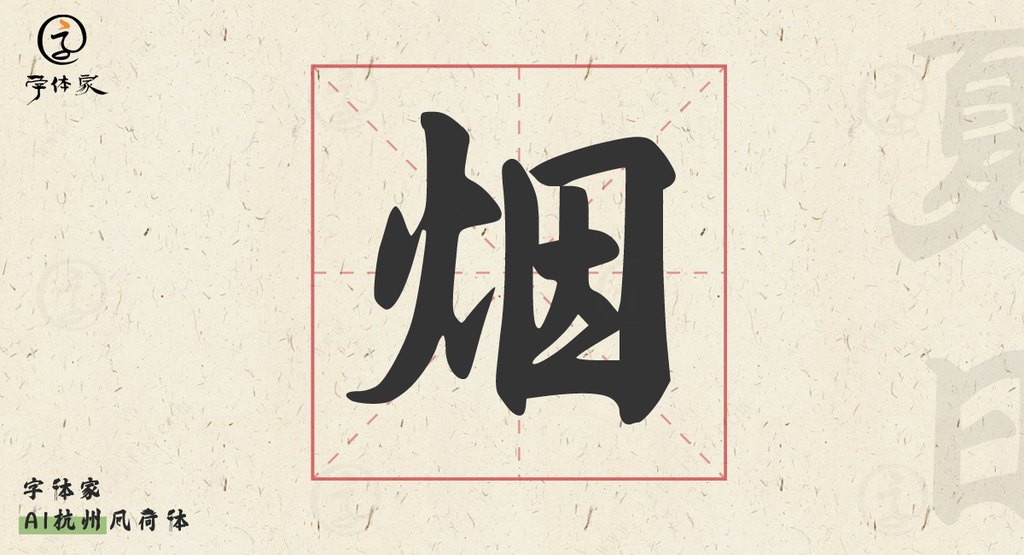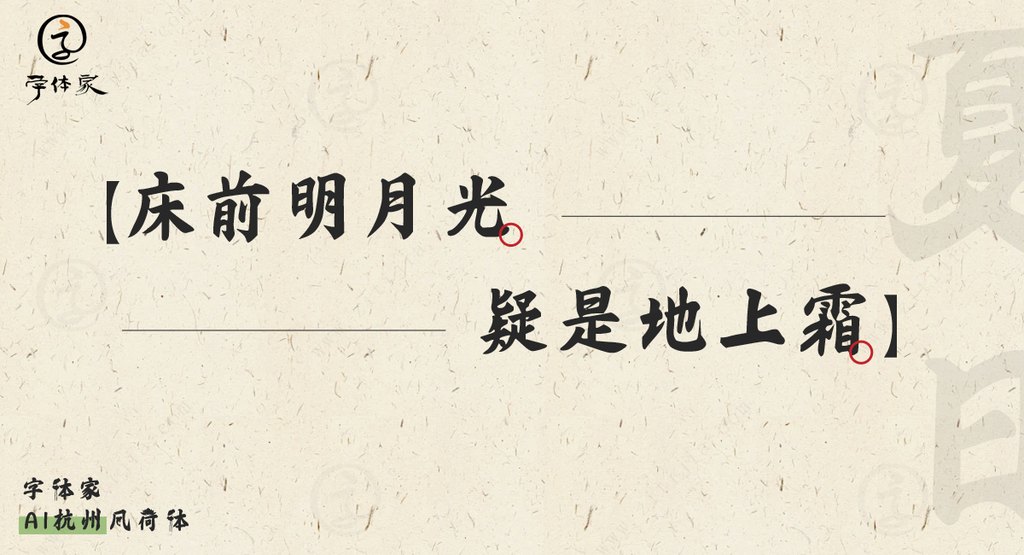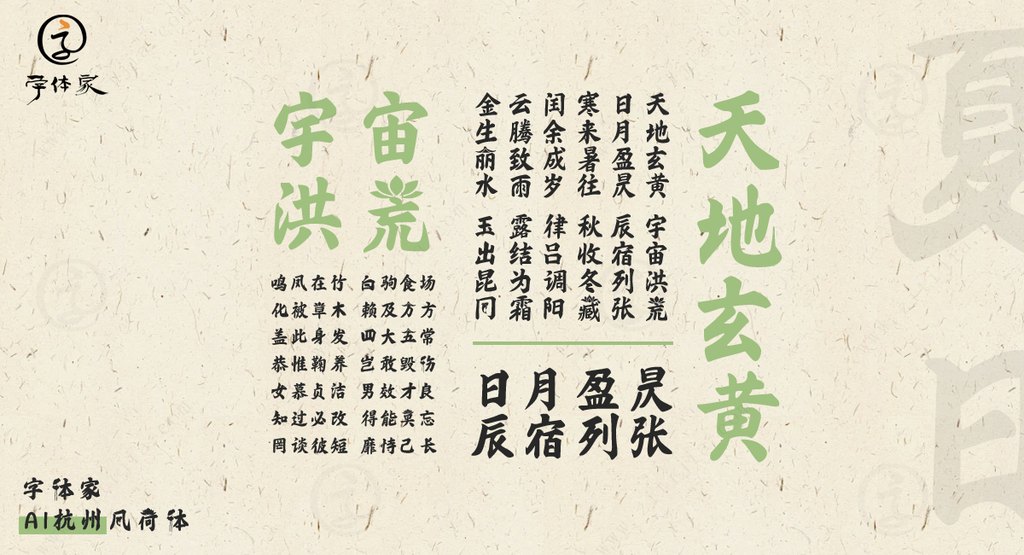
字体家AI杭州风荷体:带你领略西湖夏日的韵律
每个城市都有它的灵魂,而杭州的灵魂,可能藏在那一池荷叶、一缕酒香中。那么,当我们将这份灵魂融入到书法设计中,它会是怎样一幅动人的画卷呢?让我为大家介绍一种极具诗意的字体——字体家AI杭州风荷体。
源起:曲院风荷的传奇
杭州西湖十景之一的曲院风荷,便是这款字体灵感的起源。在南宋时期,这里曾有一座官家酿酒作坊,产出的美酒声名远扬。据说,当年每当夏日微风徐来,酒香与荷香便在空气中交织,令人陶醉不已。如此富有诗意的历史背景,自然成了杭州风荷体的设计灵感。
设计:字里行间的荷花风情
说到杭州风荷体,最引人注目的便是它那独具匠心的设计细节。设计师巧妙地把“亻”设计成了荷叶的形状,大概是想让人感受到夏日荷叶的清凉。再看看“艹”的部分,犹如一朵盛开的荷花,为文字增添了一份生命的活力。部分横笔画被设计成亭子的形状,仿佛在诉说古时苏堤旁那悠悠的浪漫情怀。
应用:古风设计的绝妙选择
如果你是一个喜欢古风的设计师,这款字体无疑是你创作时的绝妙选择。不论是古风包装的典雅表达,还是手绘海报的文化底蕴,杭州风荷体都能为你的作品增色不少。甚至在漫画领域,这款字体同样能为画面增添几分独特的气息。
结语:承载文化的现代艺术
在信息化的今天,我们总是期望通过更现代的方式去表达传统的韵味。字体家AI杭州风荷体正是这样一个成功的例子。它不仅是一种艺术字体,还承载着杭州文化的精髓。无论你是要制作网页设计,还是平面设计,这款字体都值得你一试。
在中国传统文化与现代设计碰撞出火花的同时,我相信,这款字体不仅能带给你视觉上的享受,更会为你开启一场关于杭州的如梦旅程。